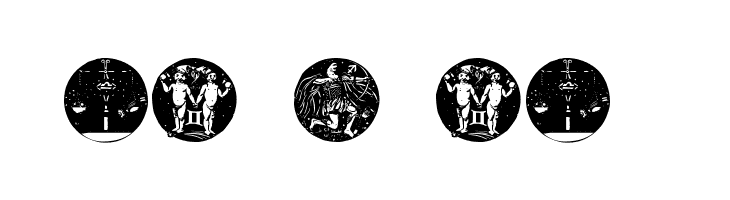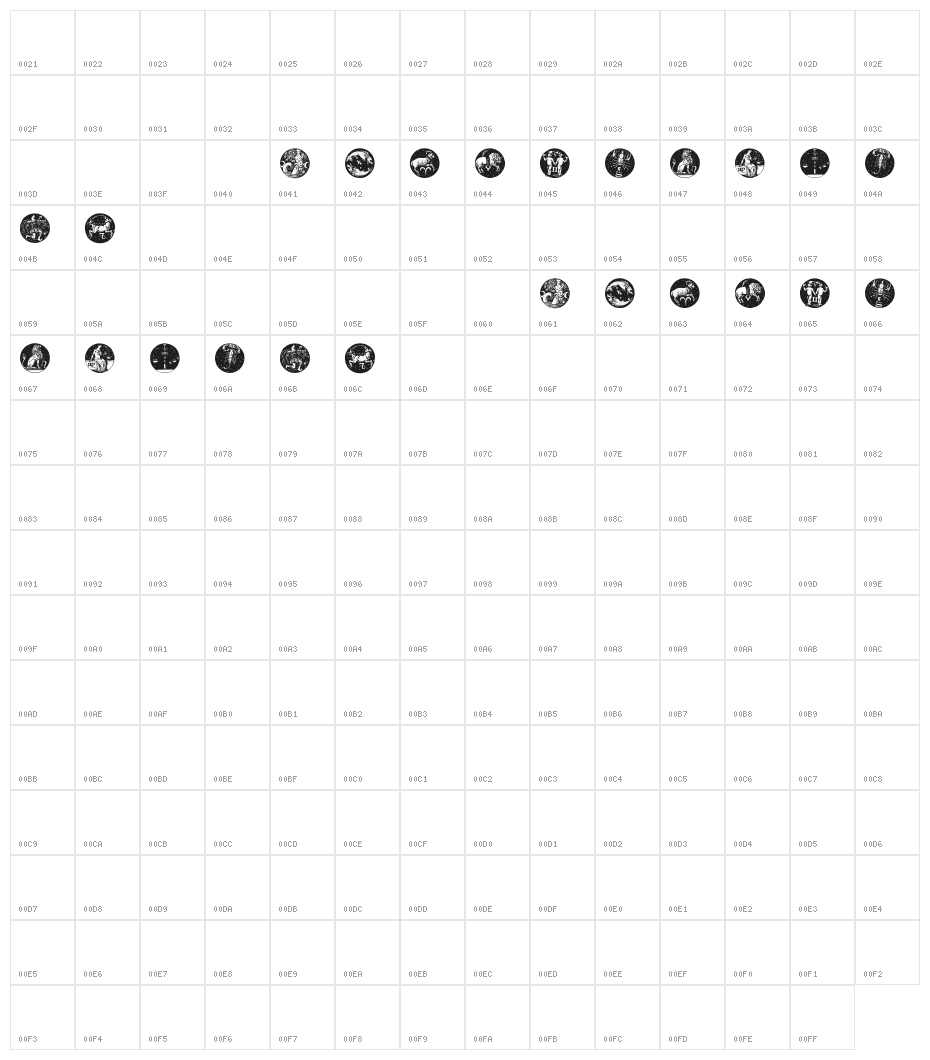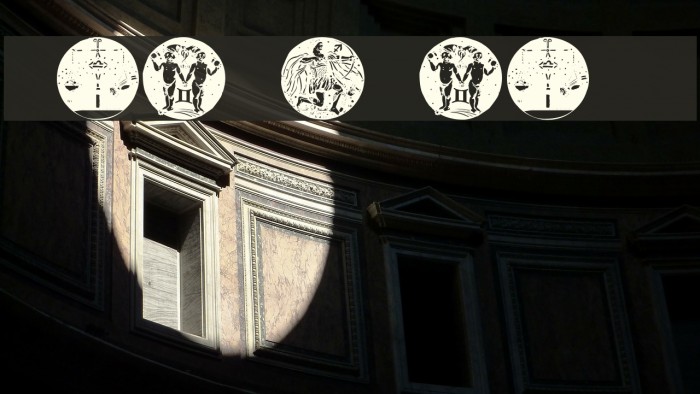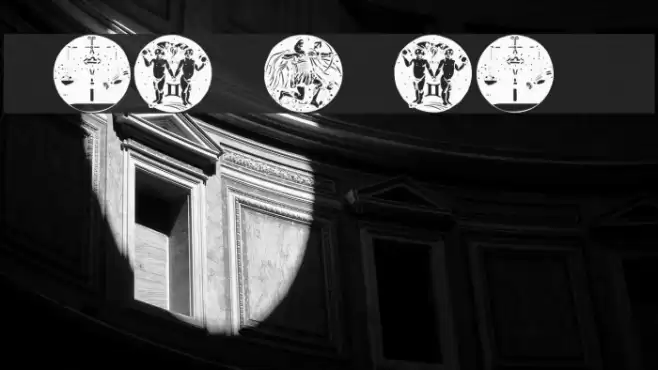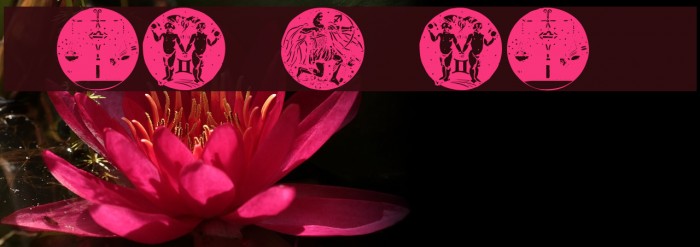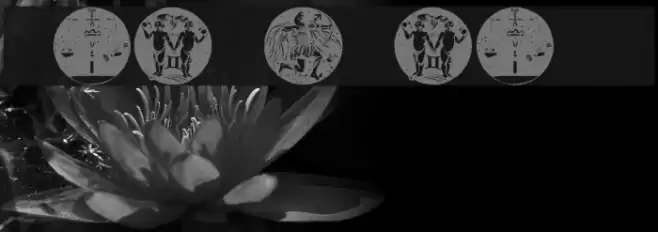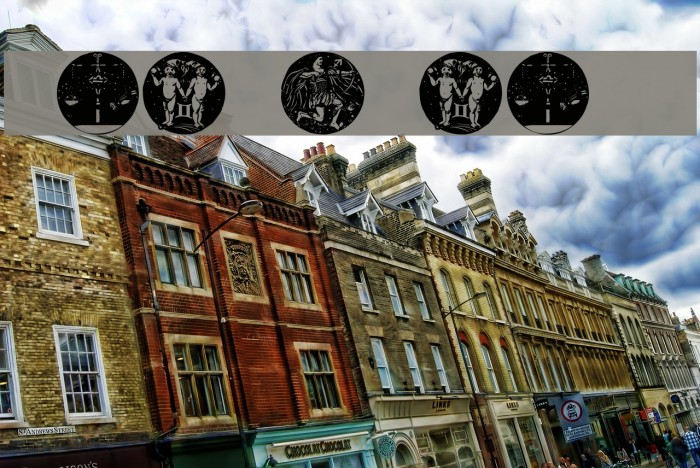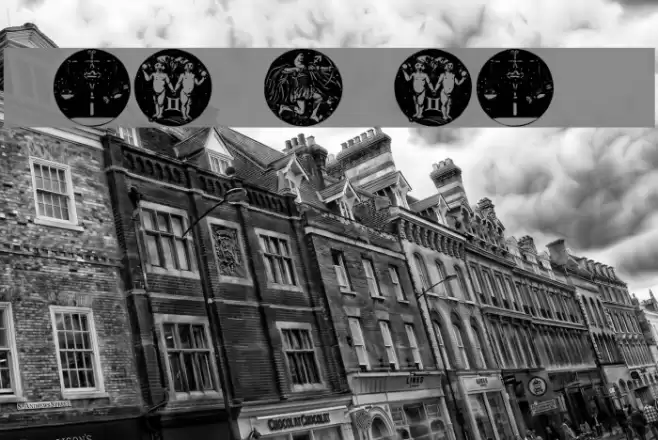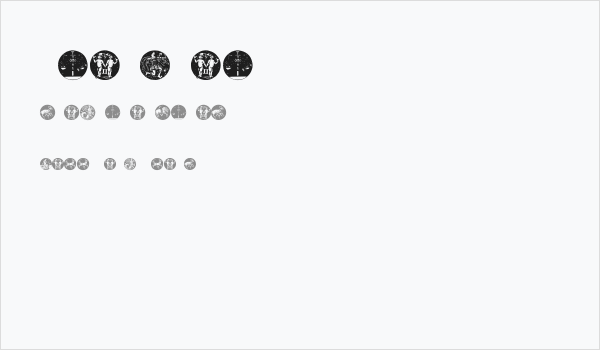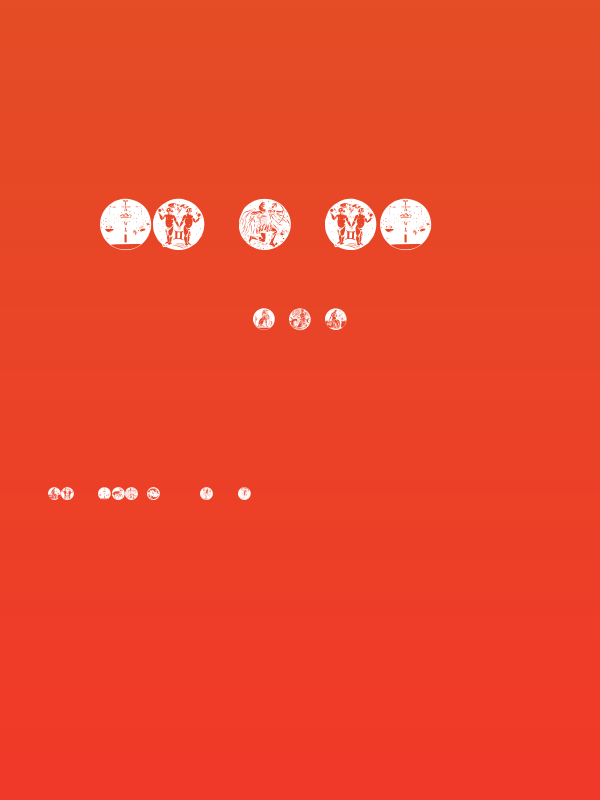
Tierkreis 5 Font
| 全体的なスタイル | Decorative, Mystical, Illustrative |
| 用途 | Logos, Headlines, Posters, Themed graphics |
| おすすめプロジェクト | Astrology posters, mystical book covers, themed invitations, decorative headings, tarot or horoscope materials. |